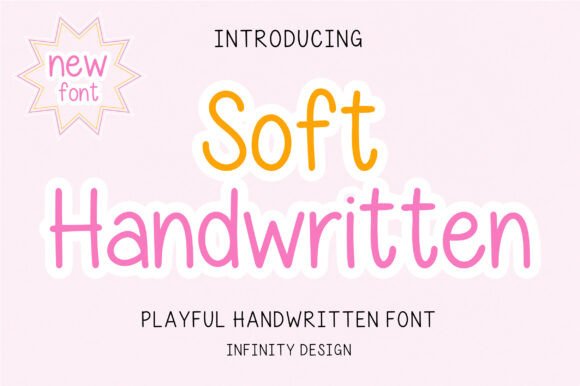
Soft Handwritten
Jika anda sedang mencari aset berkualiti tinggi seperti Soft Handwritten, pakej premium ini merupakan pilihan yang hebat untuk projek kreatif anda.
Sama ada anda mencipta produk POD (Print on Demand), jemputan perkahwinan atau grafik media sosial, Soft Handwritten amat bersesuaian.